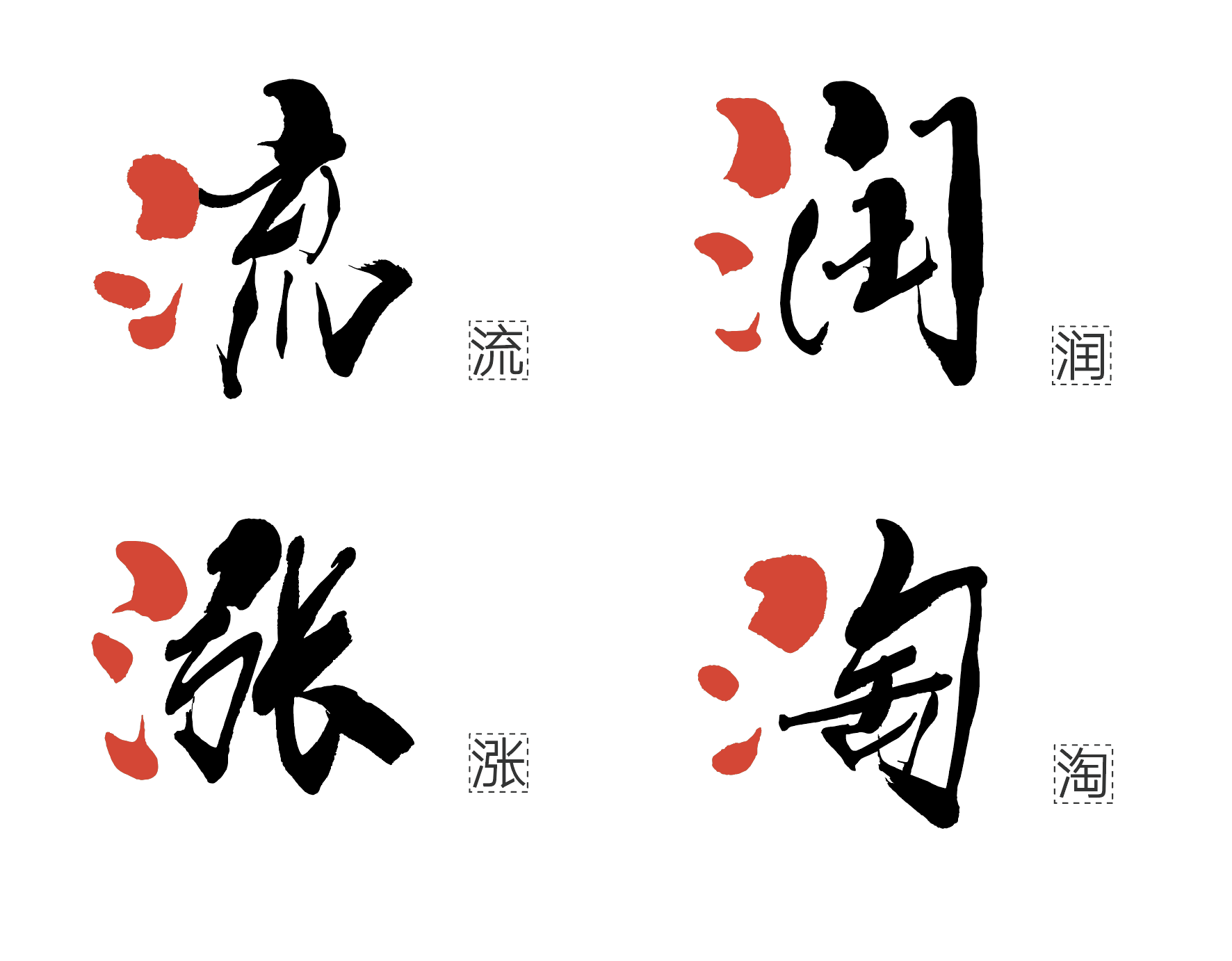
汉仪SIJIA体字体介绍,一款颇有记忆点的手写字体
汉仪SIJIA体 | 背景介绍
汉仪SIJIA体由原创写字人、插画师、平面设计师王思佳创作。
汉仪SIJIA体将传统书法与现代设计完美融合,集博大深沉的书法文化与时尚潮流于一体,既拥有文学艺术涵养,又有着前卫的创造力,适用于各类商业包装,能将品牌价值完美呈现,并能很好地凸显产品的与众不同。
汉仪SIJIA体 | 字形特点
汉仪SIJIA体的横画笔势均向右上方倾斜,字迹飞扬,字形气势整齐统一,增强了其排版效果的力量感和节奏感。
汉仪SIJIA体字形斜中求稳,重心一致,这使得其在组合排版使用时效果更佳。
汉仪SIJIA体 | 笔画特点
汉仪SIJIA体笔画粗细对比明显,组合搭配富有强烈的节奏感。以 101pt字号的“勇”字为例,最细与最粗笔画的粗度比能达到1:5。
汉仪SIJIA体结体俊逸自如,字的笔画根据不同位置作出灵活多样性的改变。下笔收笔,起承转合,多顺势而为,潇洒多姿。以偏旁为例,虽同为左右结构却有不同的形态。
汉仪SIJIA体起笔有停顿,点画饱满,转折圆润,新颖时尚,强烈的王思佳个人风格,贯穿了字体的转折笔画间。
汉仪SIJIA体 | 西文字母
汉仪SIJIA体西文字母的设计,参考并借鉴了中文笔画的书写方式,较好的还原了书法的手写感,使中西文的搭配和谐统一。
汉仪SIJIA体 | 排版效果